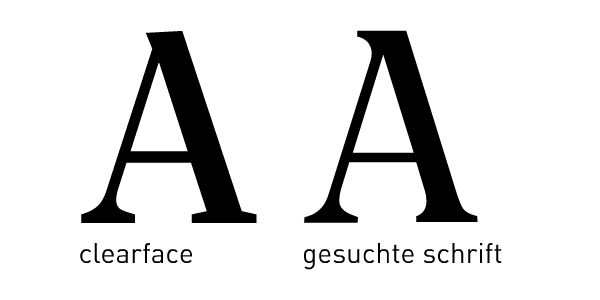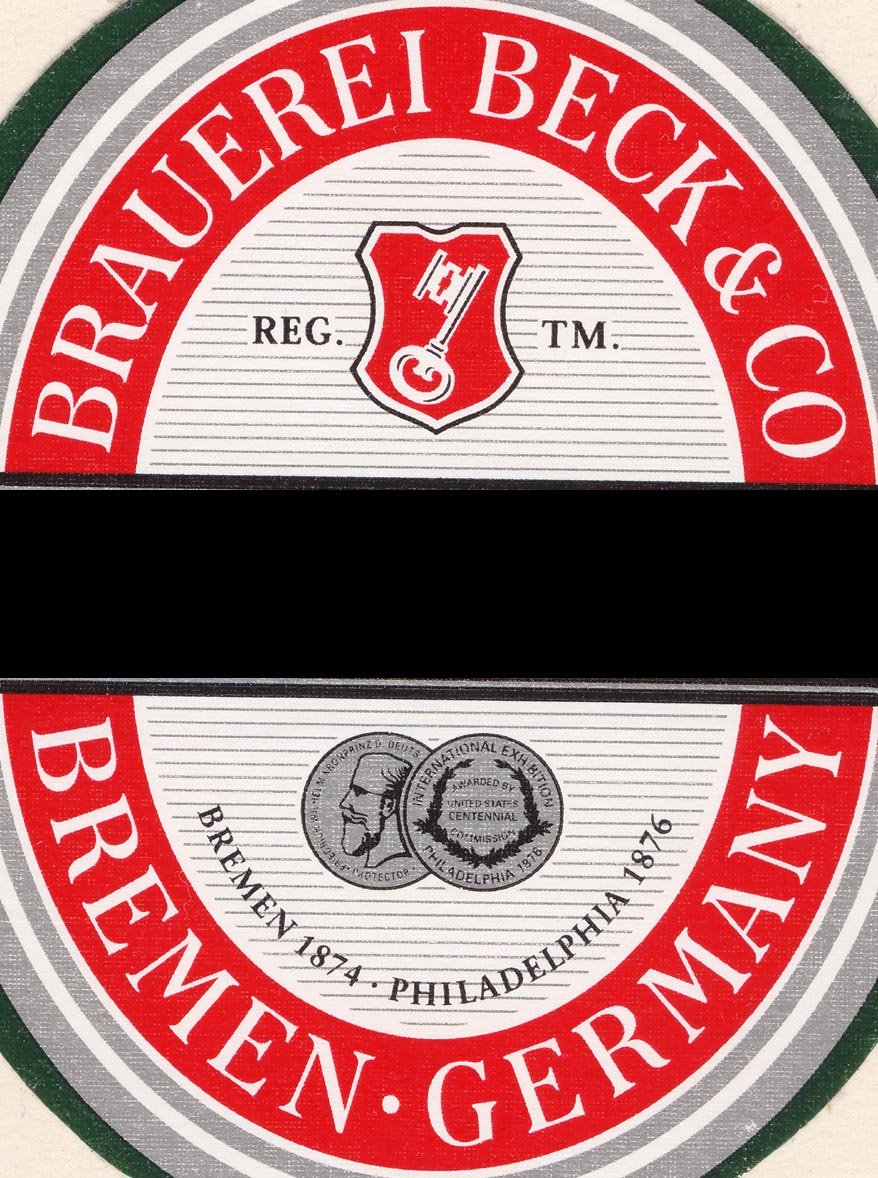
Serifenschrift ähnlich Clearface gesucht
Ich suche eine Serifenschrift, die eigentlich exakt so aussieht wie die Clearface, bis auf die Tatsache, dass die Serifen nicht einfach an den Stamm stoßen, sondern klar erkennbar ein Radius im Übergang von Serife zu Stamm (Kehlung) vorhanden ist.
WTF (WhatTheFuckingFont) lieferte keine brauchbaren Ergebnisse. Bei identifont.com bin ich trotz gewissenhafter Beantwortung der Fragen auch nicht schlauer geworden.
Um den Unterschied zu verdeutlichen noch ein Bild:
Ich suche eine Serifenschrift, die eigentlich exakt so aussieht wie die Clearface,
Soo exact finde ich das gar nicht. Die Verhältnisse der Strichbreiten sind schon noch recht unterschiedlich.
Um den Unterschied zu verdeutlichen noch ein Bild:
Hast du vielleicht noch ein paar interessante Buchstaben RagfeQw oder sowas Interessantes – »Hamburgefonts« wird auch immer gern genommen.
Das Problem ist, dass ich keine unverzehrte Variante zur Verfügung habe. Und dann auch nur ein paar Versalien. Die Strichbreiten zur Clearface variieren, aber die markanten Buchstaben stimmten von ihrer Form her alle mit der Clearface überein. Meine Hoffnung besteht halt darin, dass irgendein Schnitt der gesuchten Schrift schon passen wird. So wie boldWide oder sowas..
Es ist die Schrift auf dem roten Fond des Beck's Etiketts:
Mh, naja..wie gesagt: Clearface ist auch ähnlich. Aber eben nicht die Schrift, die ich suche. Sollte schon genau die sein.
Utopia ist auch nur so ähnlich, gell? Müsste aber auch was Älteres sein, sag ich als geborener Bremer mal so, denn die Becks-Schriften sahen schon immer so aus, glaube ich ...
Nachtrag: Früher war's, glaube ich (gaaanz dunkle Erinnerung), die Walbaum. Vielleicht doch die Utopia?